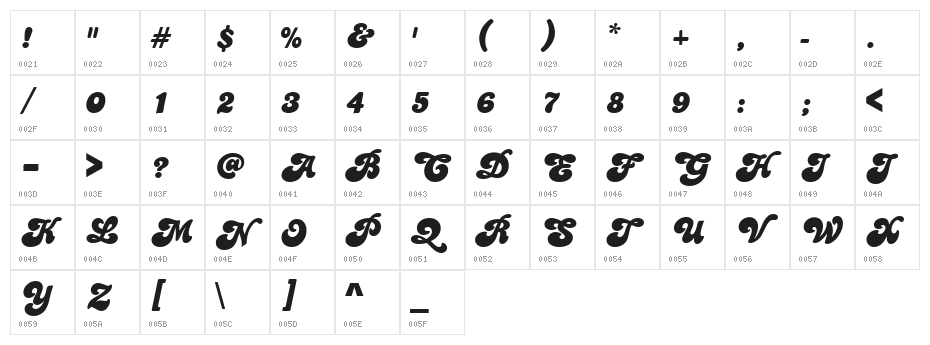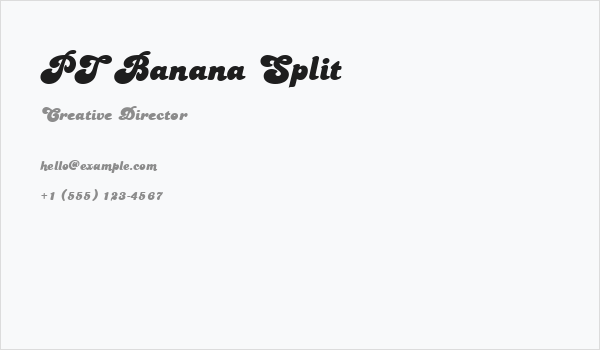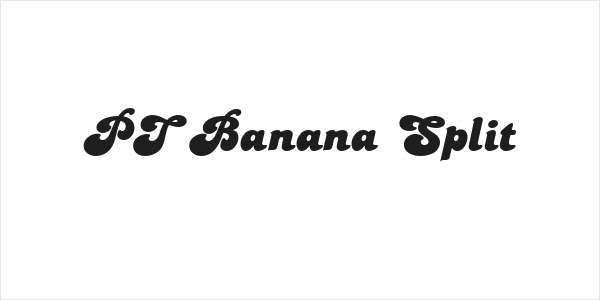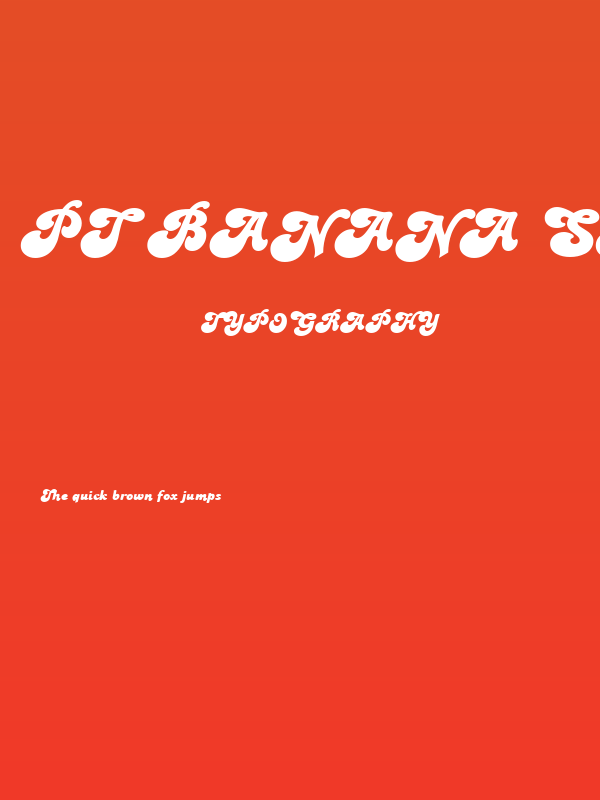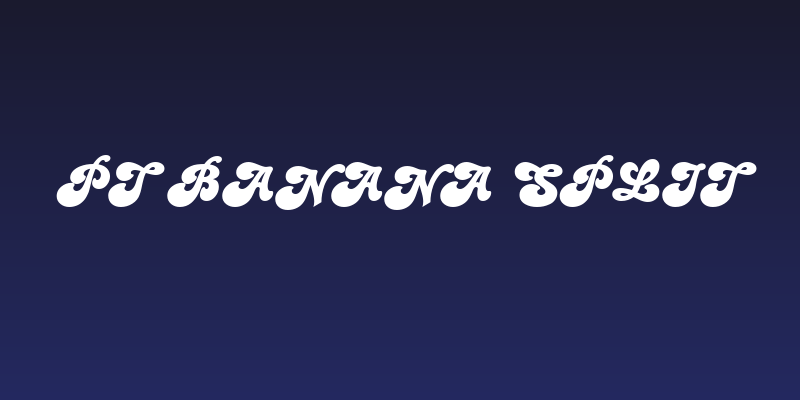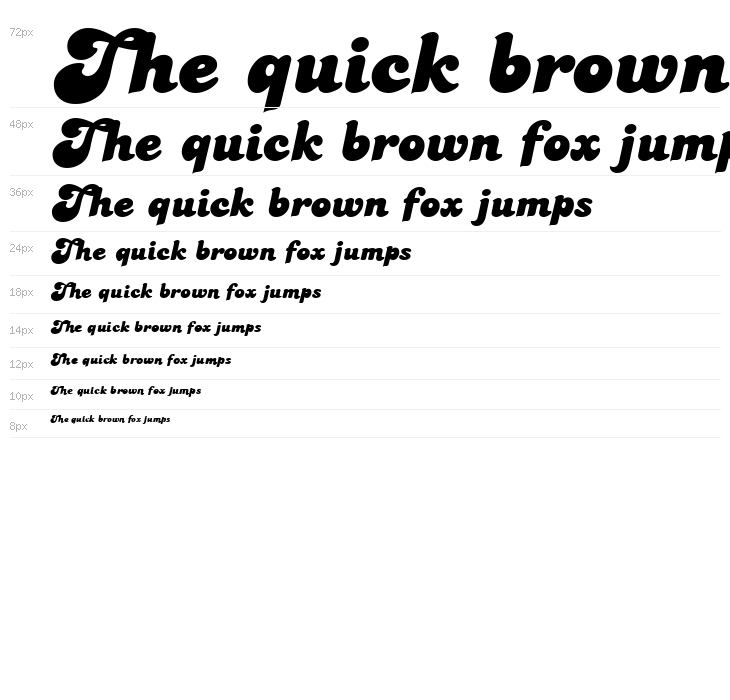
PT Banana Split Font
| Name | PT Banana Split |
| Gewicht | Normal |
| Kategorien | Decorative |
| Gesamtstil | Playful and Whimsical |
| Anwendungsfall | Logos, Headlines, Posters |
| Vorgeschlagene Projekte | Ideal for children's books, playful branding, party invitations, and creative posters. |